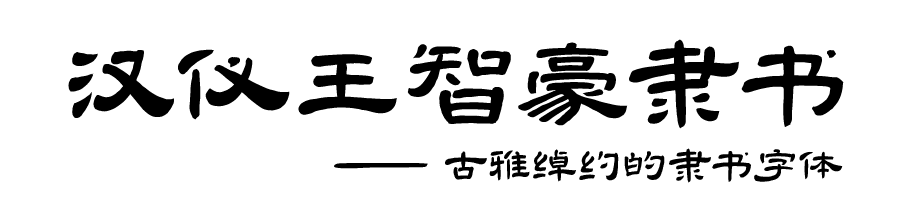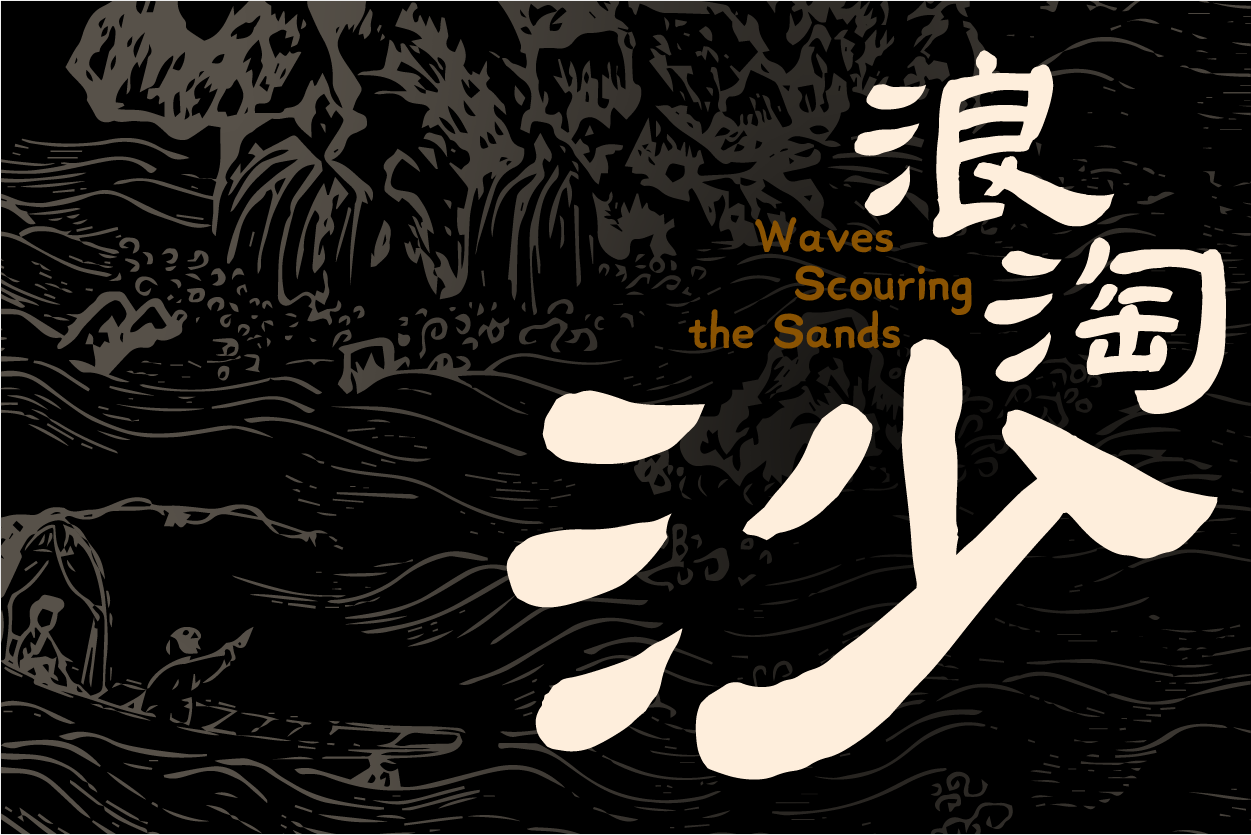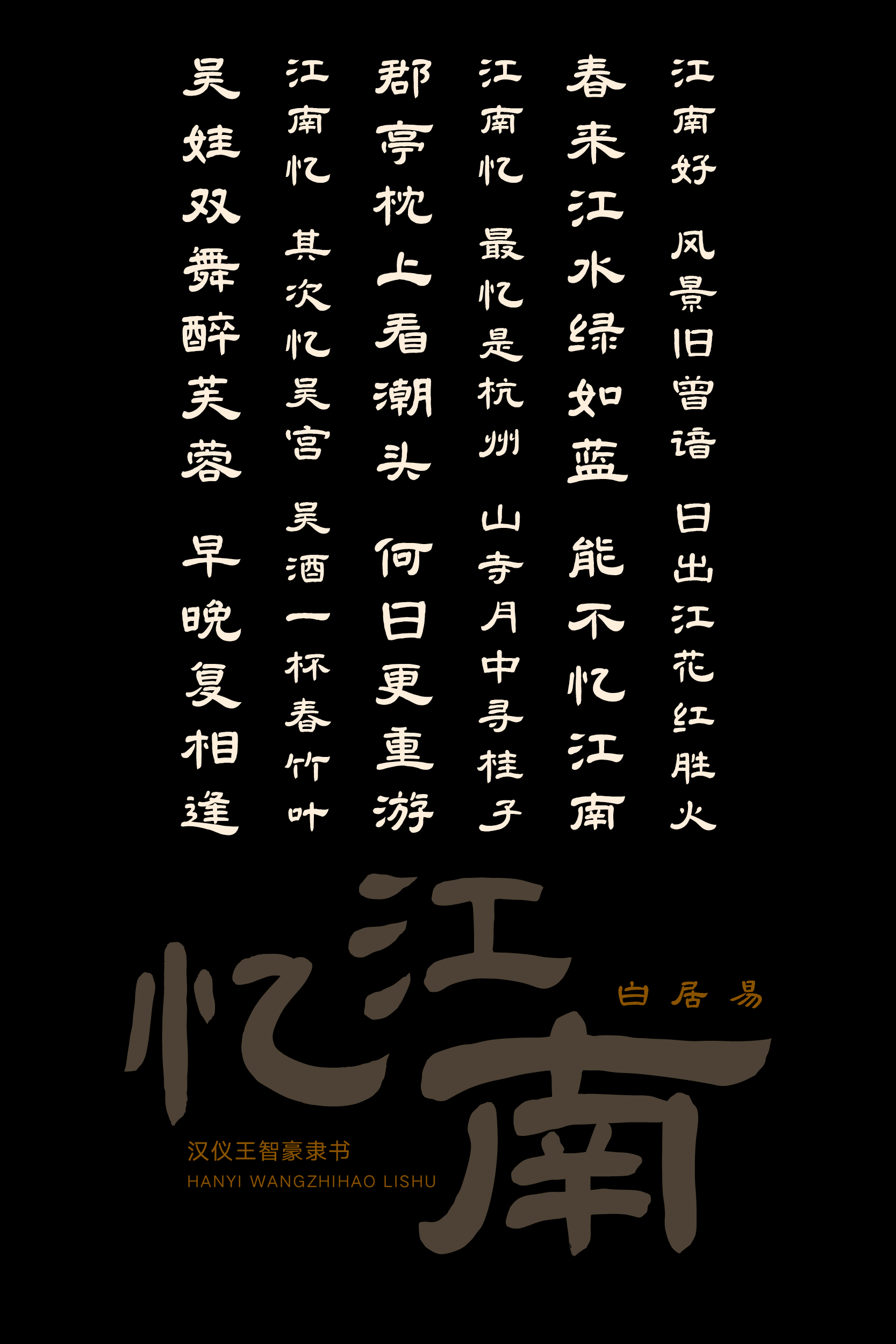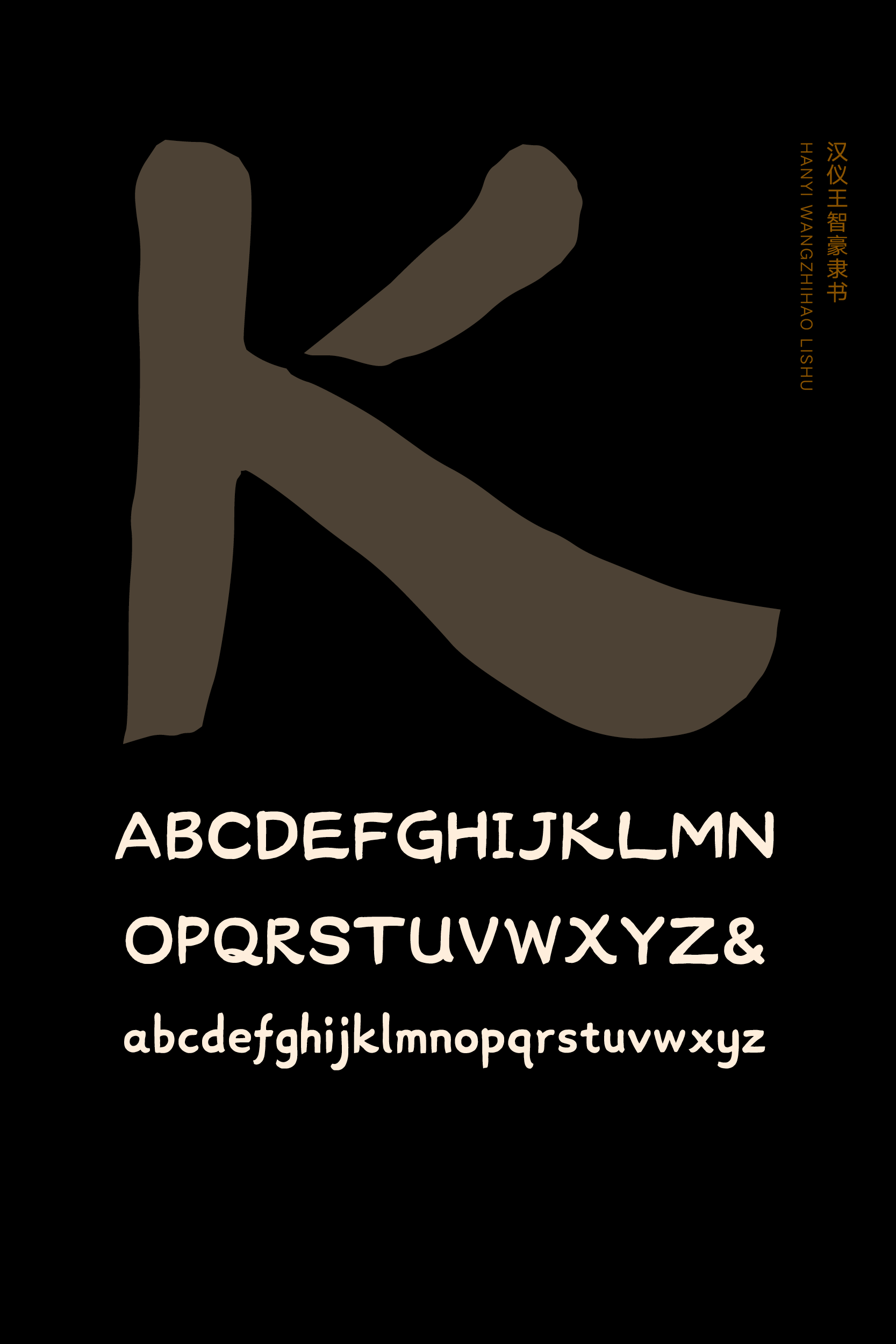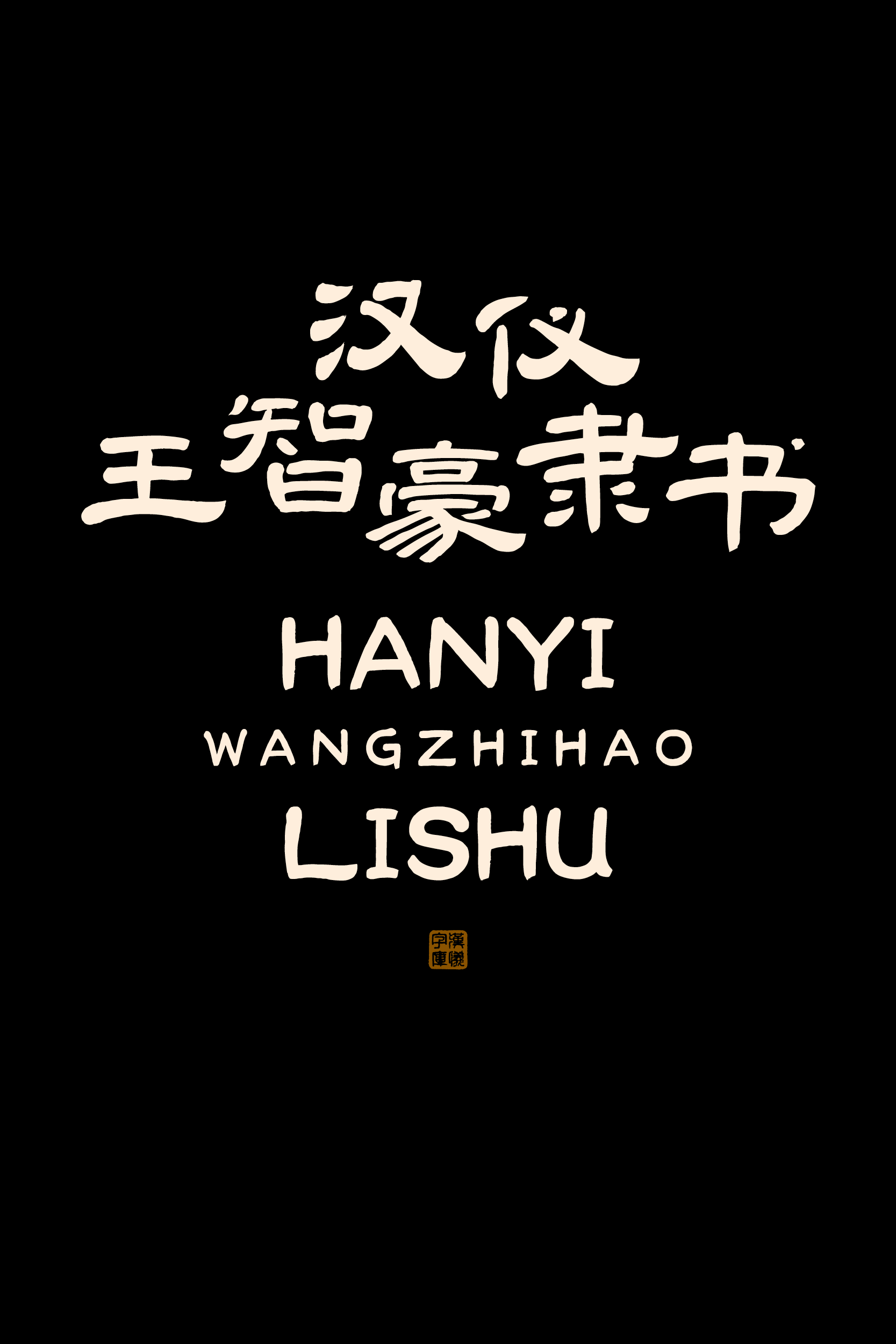
汉仪王智豪隶书字体介绍,汉仪王智豪隶书设计灵感
汉仪王智豪隶书 | 古雅绰约的隶书字体
汉仪王智豪隶书是由汉仪字库签约作者,青年书法家王智豪创作的一款隶书字体。这款字体从古代碑刻中提炼精华,并加上了作者自己的创意构思,使得这款字体既能展现出古雅气质,又能符合当代审美。这款字体可以用在文创、包装、碑刻等各种需要展现传统文化的场合。
汉仪王智豪隶书 | 结字汲古纳新
汉仪王智豪隶书以《曹全碑》为参考,吸收了此碑的诸多特点:扁平舒展、上紧下松、布白均匀、收放自如。作者将《曹全碑》的诸多特点提炼出来,并做了一定的统一规范,使得每个字形都能有一致的风格效果。
作者在创作时,有意放大了《曹全碑》笔断意连的印象。在可以断笔的位置都或多或少做了断笔处理。这一手法扩大了字形内部的白空间,营造出笔画之间的缝隙,为字体打造出一种独特的风格。
汉仪王智豪隶书 | 笔法灵动自然
这款字体以传统隶书笔法为主,基本保留了《曹全碑》的笔法处理方式,但是在轮廓处理方面,除磔、掠和部分收笔处,其余笔画外轮廓全部处理成圆角形式,使得字形更加圆润自然,排版视觉效果更加统一。
该字体笔画强化了笔画的对比,主笔夸张灵动、粗细对比明显、使得字体绰约不呆板,保持字体的和谐统一。
汉仪王智豪隶书 | 中西文匹配
汉仪王智豪隶书的西文也是由作者创作的,作者将隶书蚕头燕尾的特征融入到字体中。字形整体温润可爱,中西文搭配在一起统一和谐。
汉仪王智豪隶书 | 样张展示